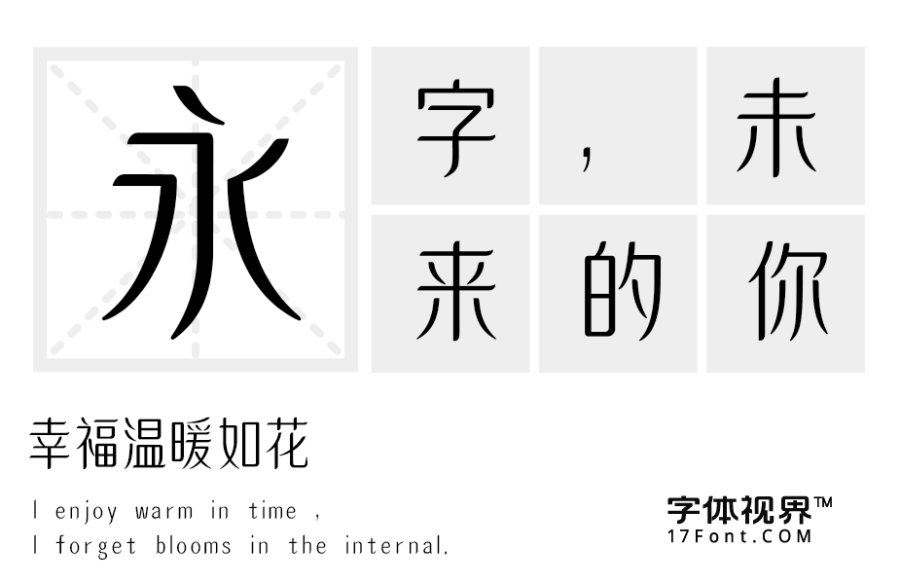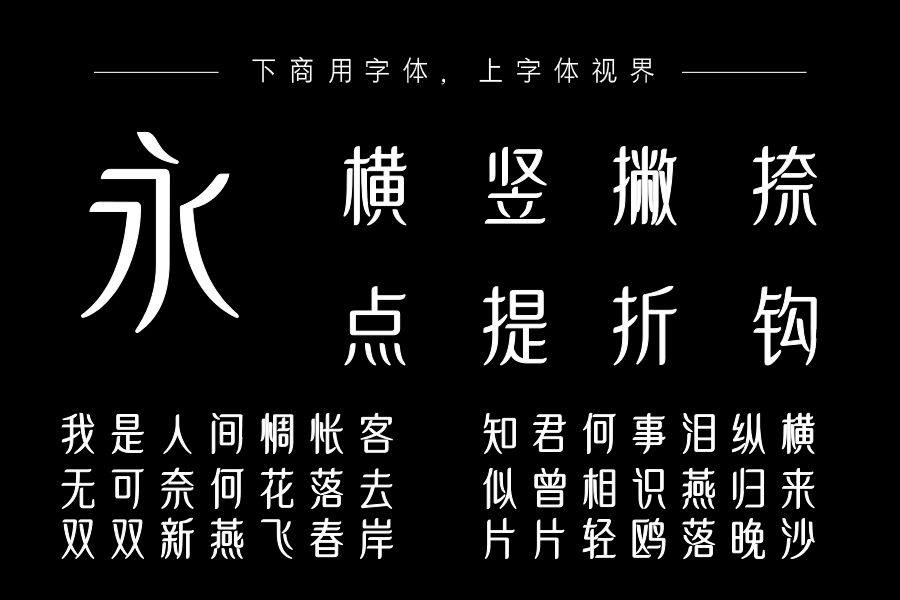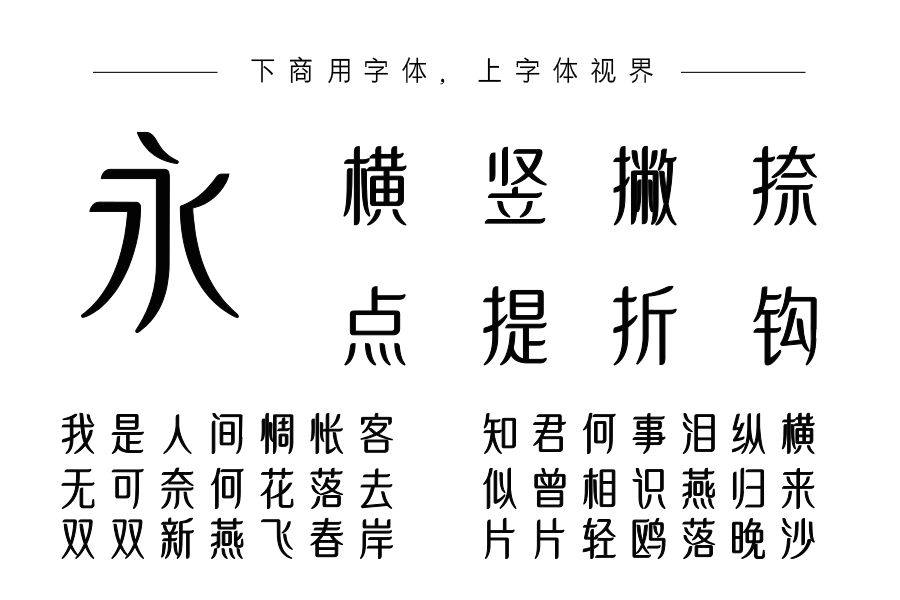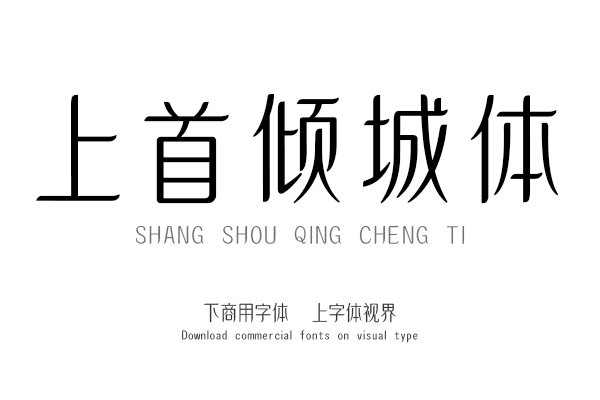
字体笔画融入了女性纤细的线条美感,横笔进行了翘脚显示了女性的俏皮之感。整体添加了倒圆处理使字体风格偏柔和,适用于搭配标志、广告标语、商业广告等高端属性。购买须知:“下载服务费”与“字体VIP”所获得字体 仅用于个人非商用, 商用请联系付费授权。本字体为电脑用字,手机没有root权限不支持直接手机换字(手机如何root,请自行百度搜索教程)。购买前请先 了解清楚后再付款 ,字体为虚拟产品无法回收 一旦购买不支持退款。